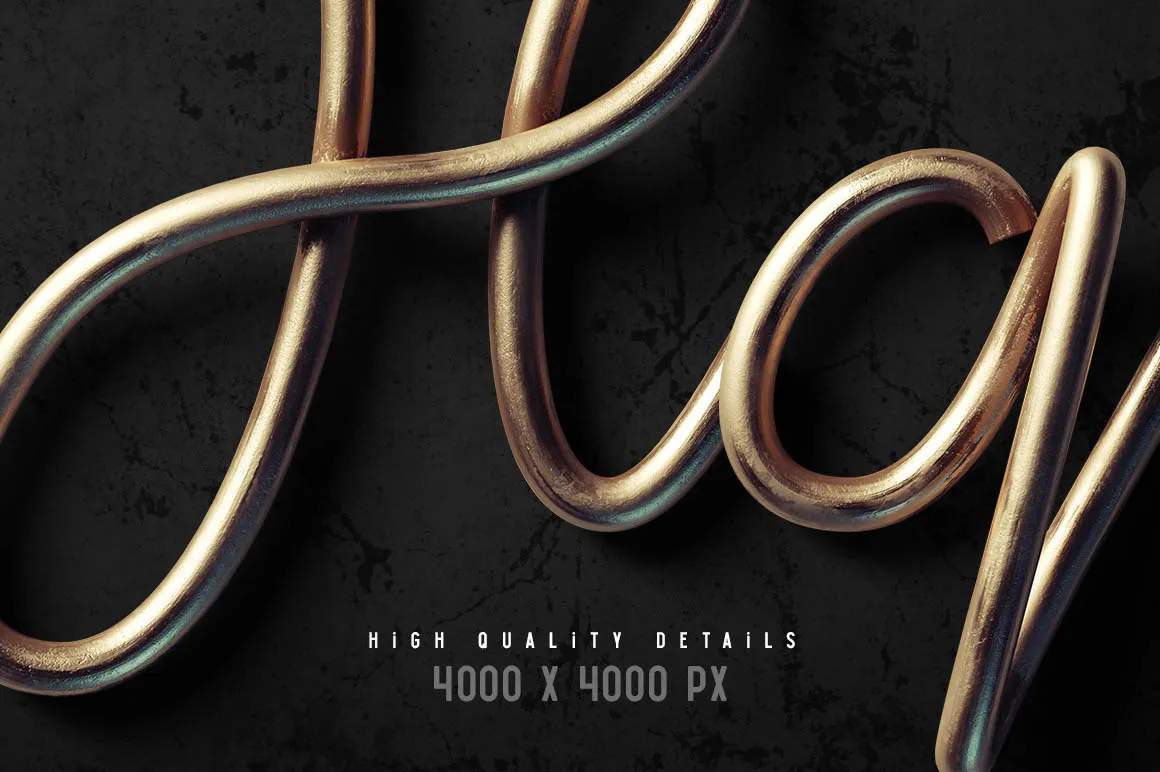
Графический Алфавит в 3D для Photoshop и Шрифты
Creative Graphic Typography — это профессиональный набор графических ресурсов, предназначенный для создания эффектных надписей в 3D-стиле. Продукт представляет собой коллекцию готовых визуальных элементов и шрифтовых файлов, которые позволяют пользователю быстро интегрировать объемную типографику в свои дизайнерские проекты. Набор ориентирован на графических дизайнеров, иллюстраторов и создателей контента, которым требуется качественная 3D-графика для оформления заголовков, рекламных материалов или цифрового искусства.
- 9 уникальных наборов для создания надписей в стиле 3D.
- Дополнительные графические элементы, которые поставляются в составе некоторых наборов для расширения возможностей оформления и кастомизации надписей.
- Инструментарий для работы с объемной типографикой, позволяющий создавать визуально сложные композиции без необходимости отрисовки каждого элемента с нуля.